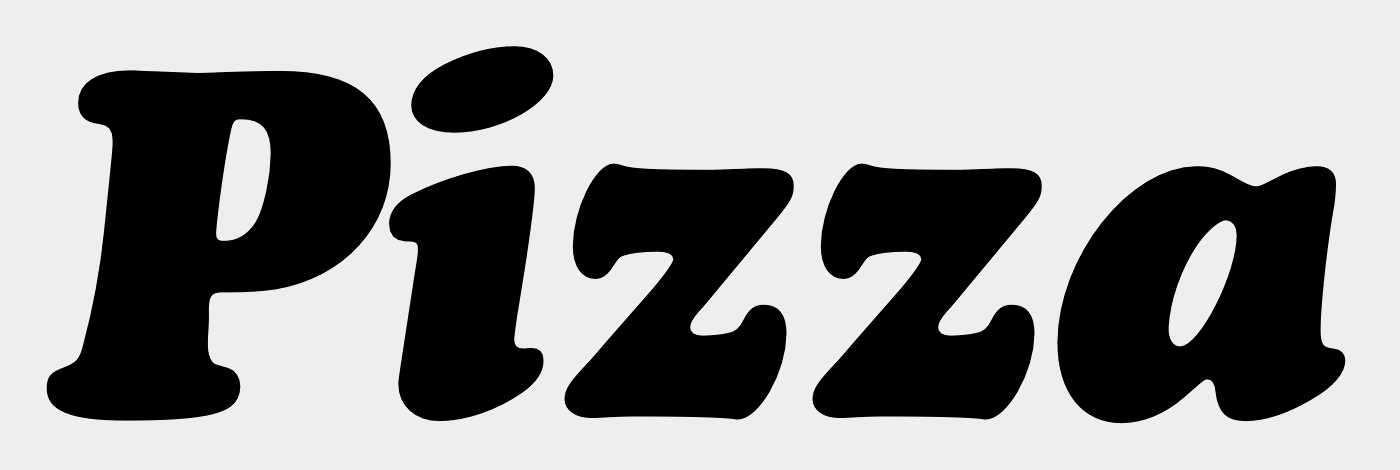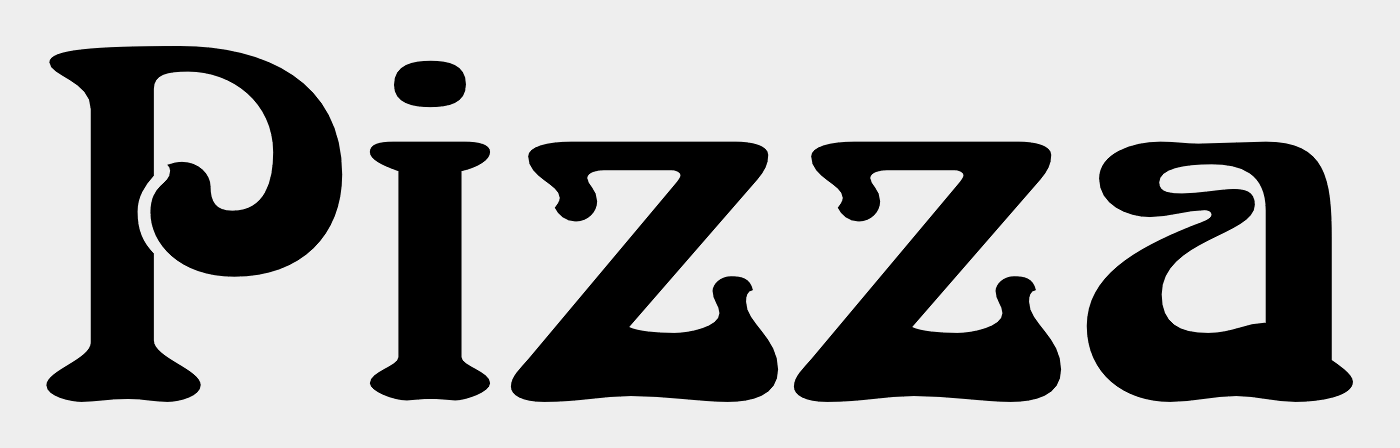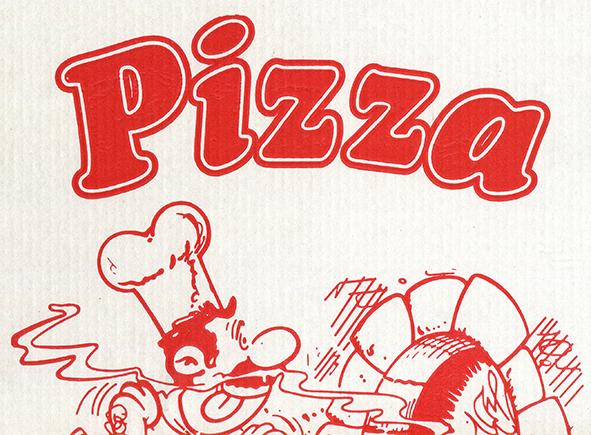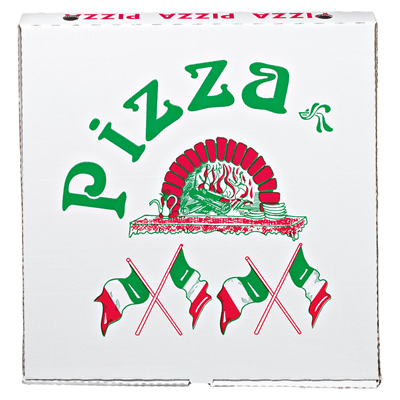
Schrift auf Pizza-Karton
für ein Mini-Projekt benötige ich den Namen der Schrift, die auf diesem Pizzakarton zu sehen ist. Ich benötige die Schrift für die Erstellung einer Illustration. Es wäre toll, wenn mir hier jemand weiterhelfen könnte.
Wie sieht es mit dieser Schrift aus? Weiss jemand welche das ist? Martin, du vielleicht nochmal?
Ursprünglich wird das mal eine Cooper Black Italic gewesen sein …